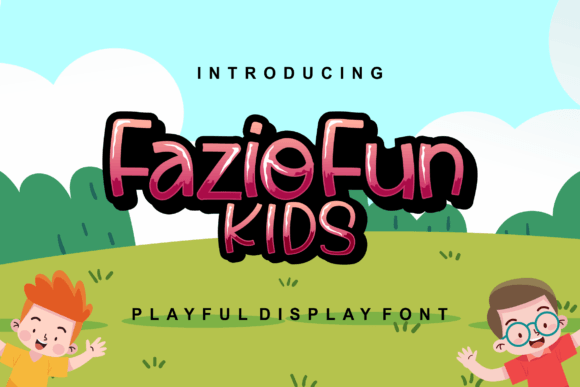
Fazio Fun
Mencari elemen reka bentuk yang sesuai boleh menjadi mencabar, tetapi Fazio Fun menawarkan koleksi luar biasa yang menaik taraf karya anda serta-merta.
Sama ada anda mencipta produk POD (Print on Demand), jemputan perkahwinan atau grafik media sosial, Fazio Fun amat bersesuaian.